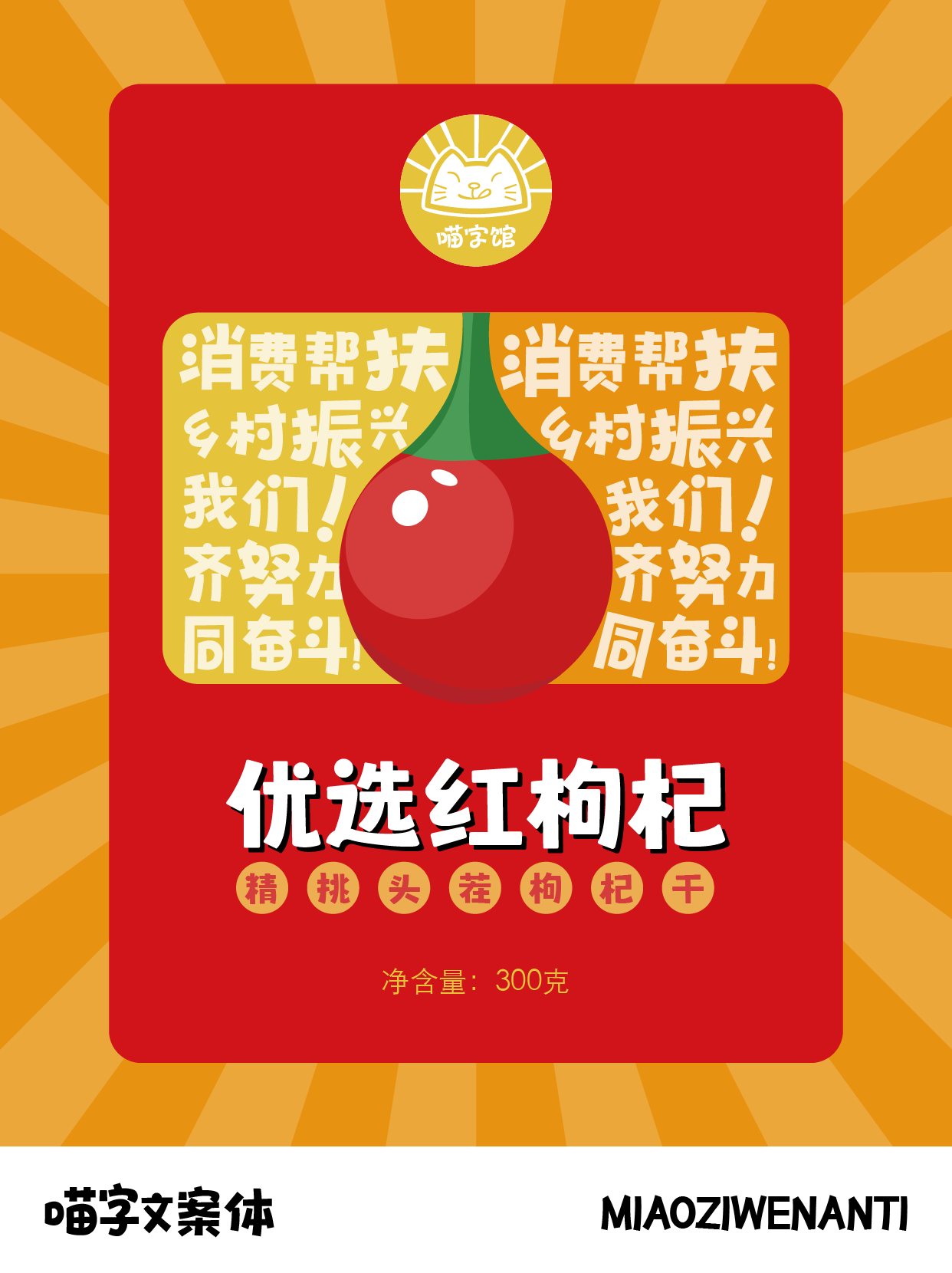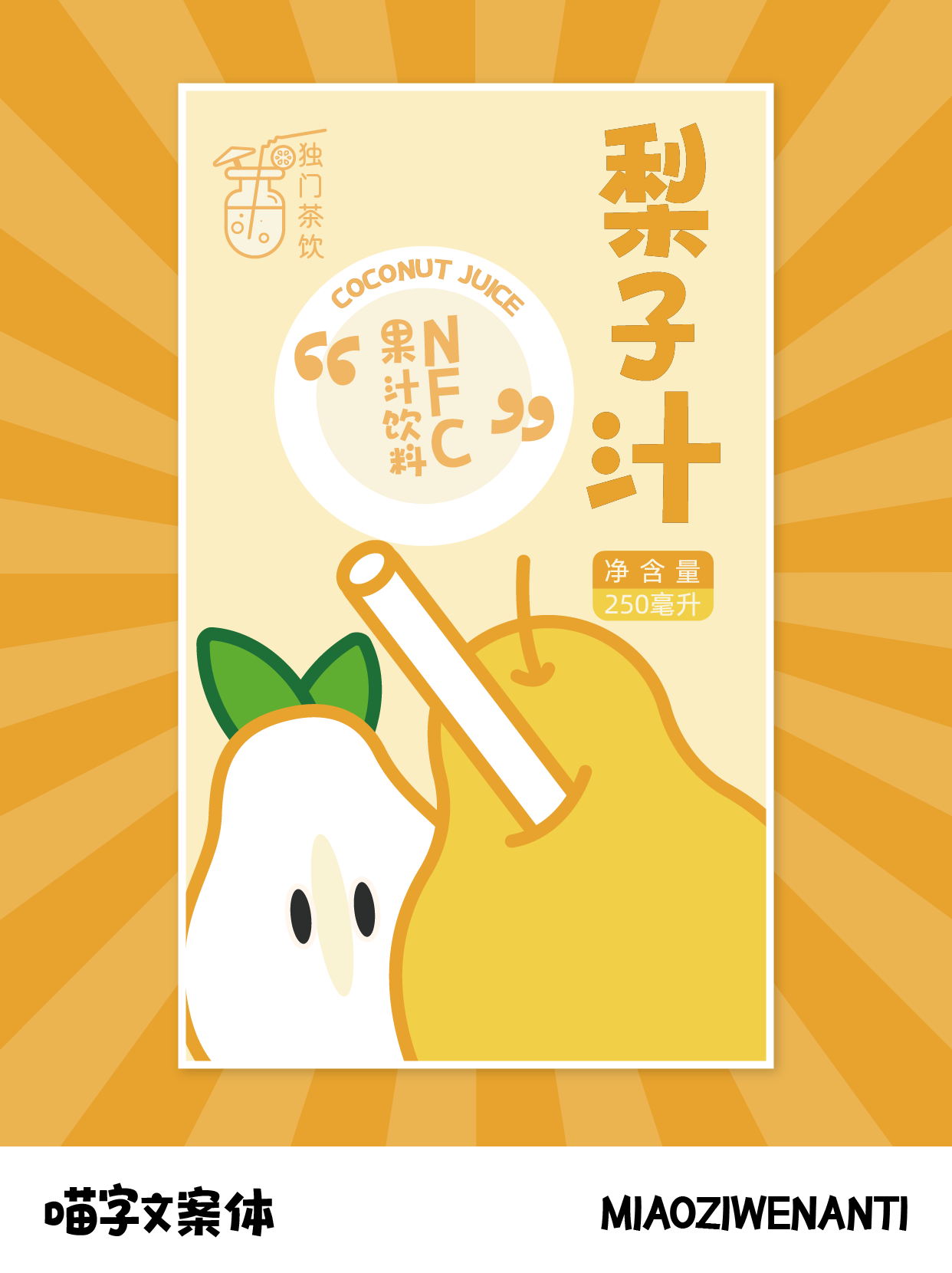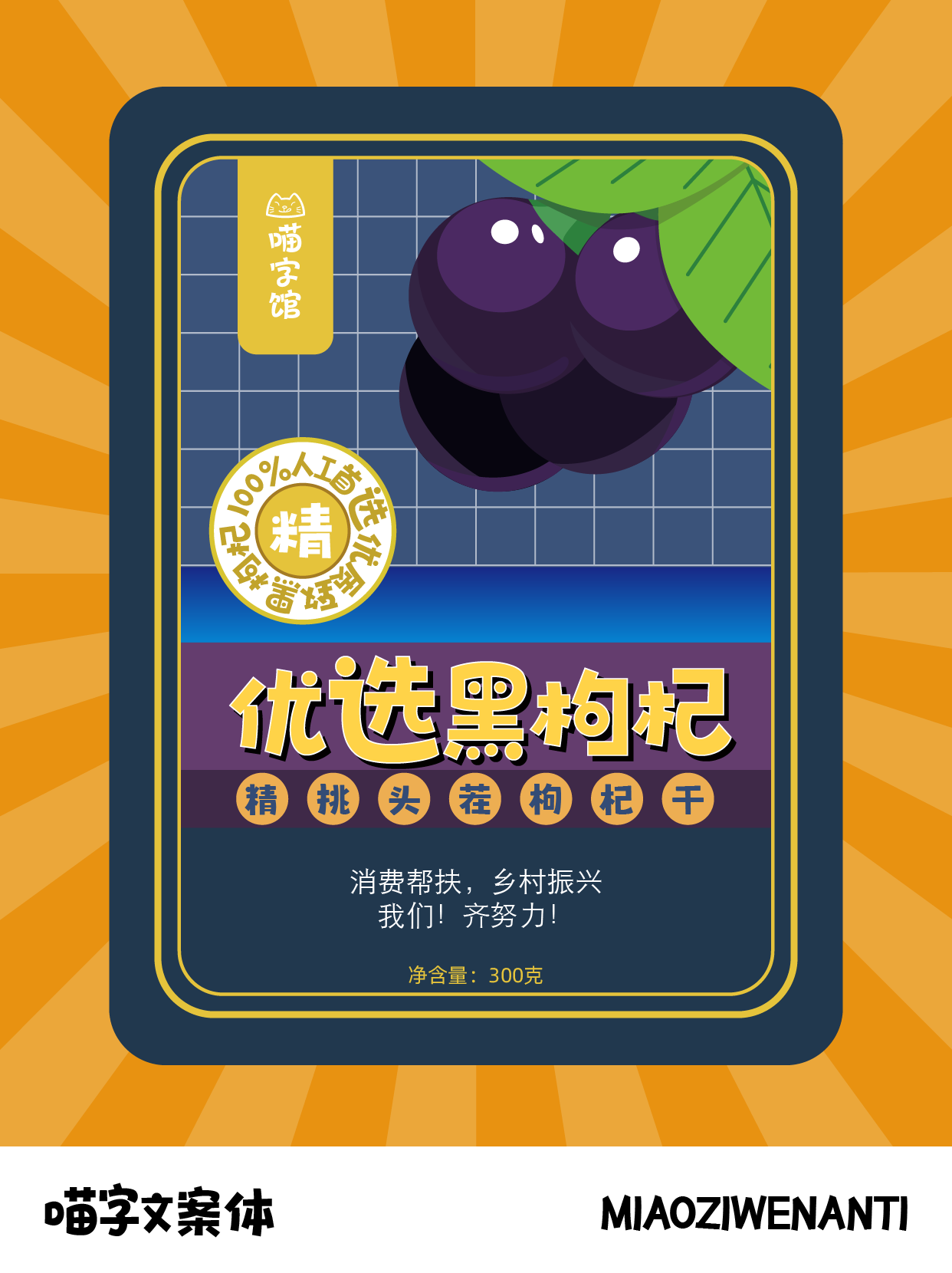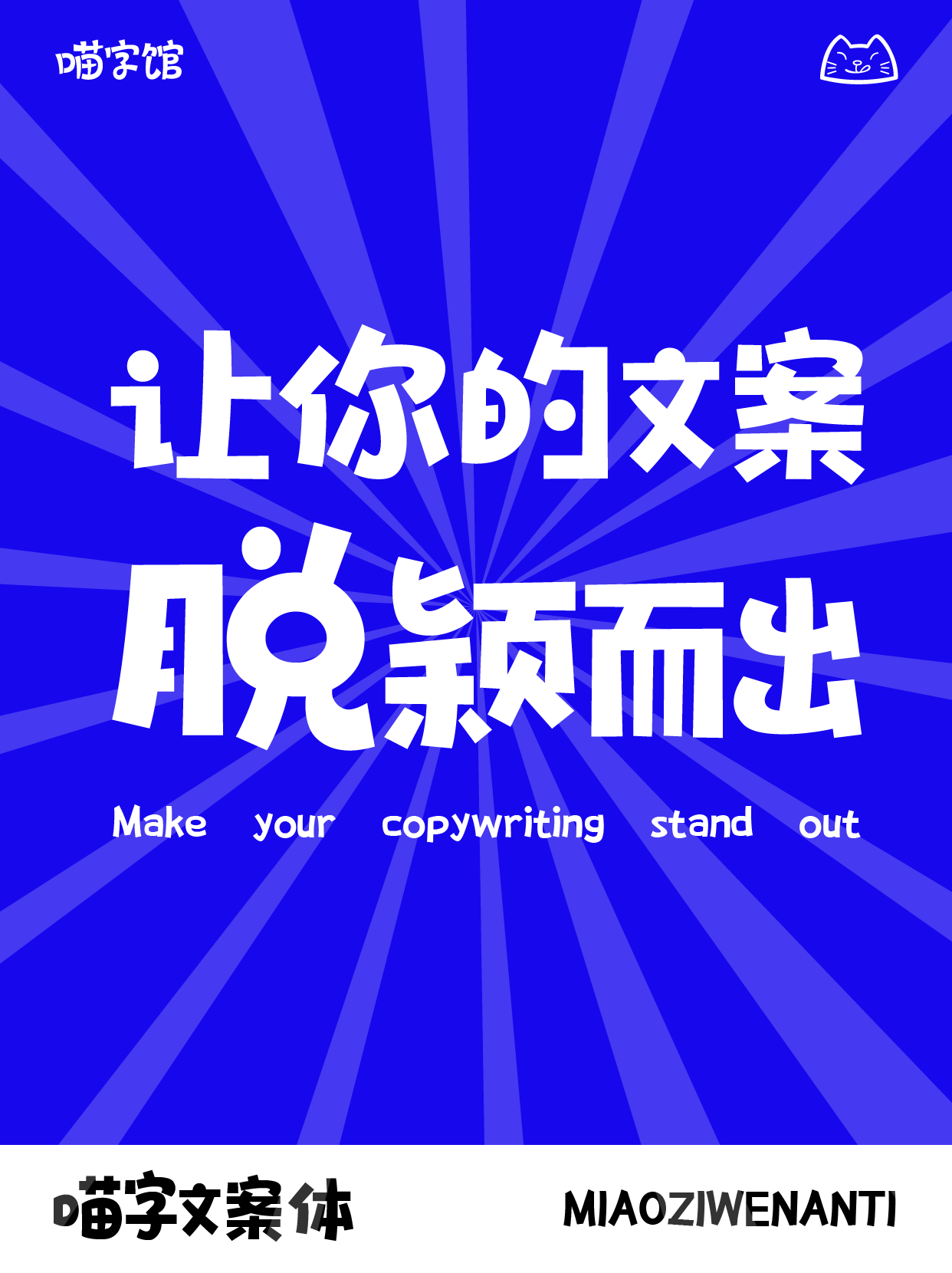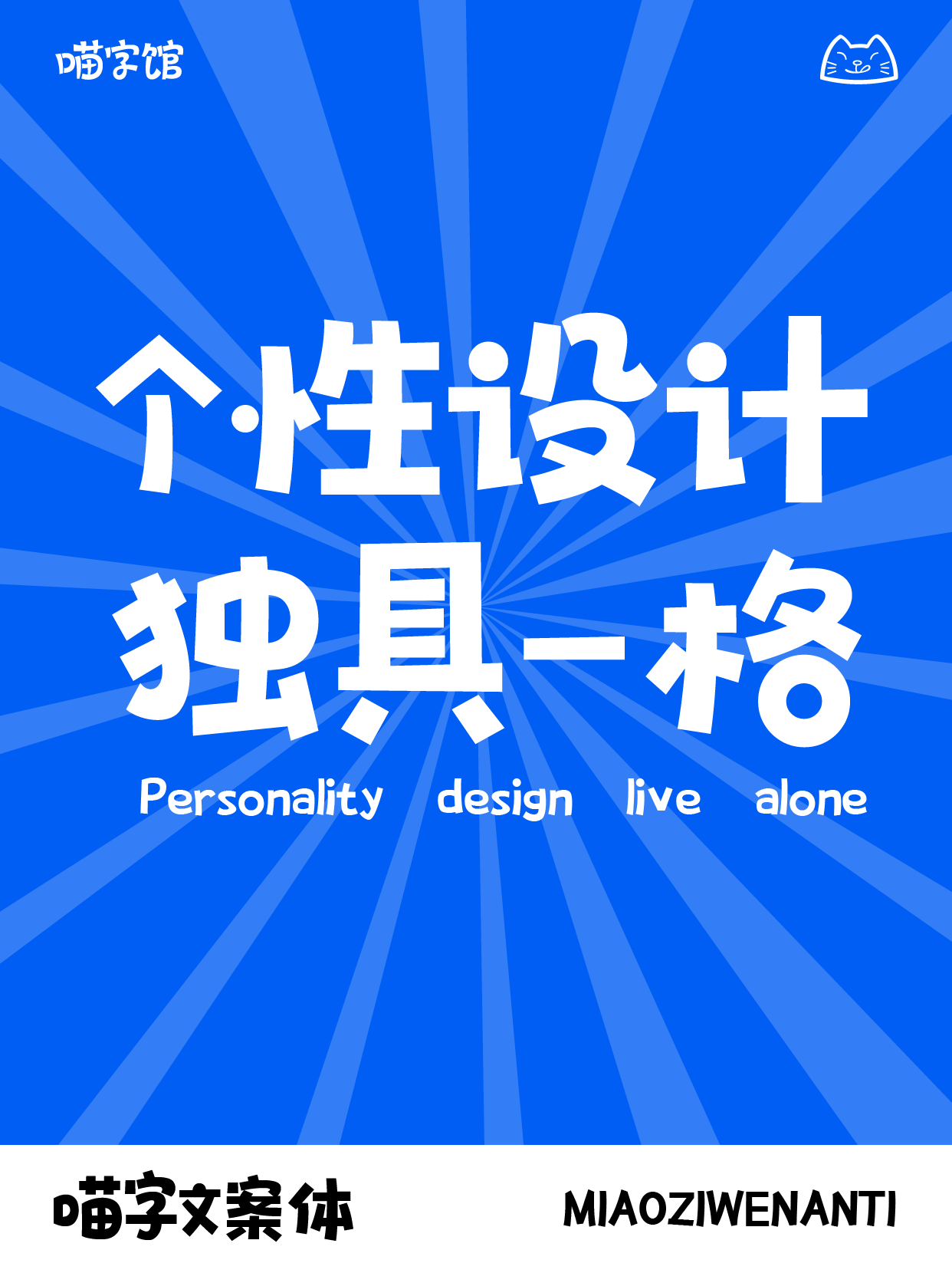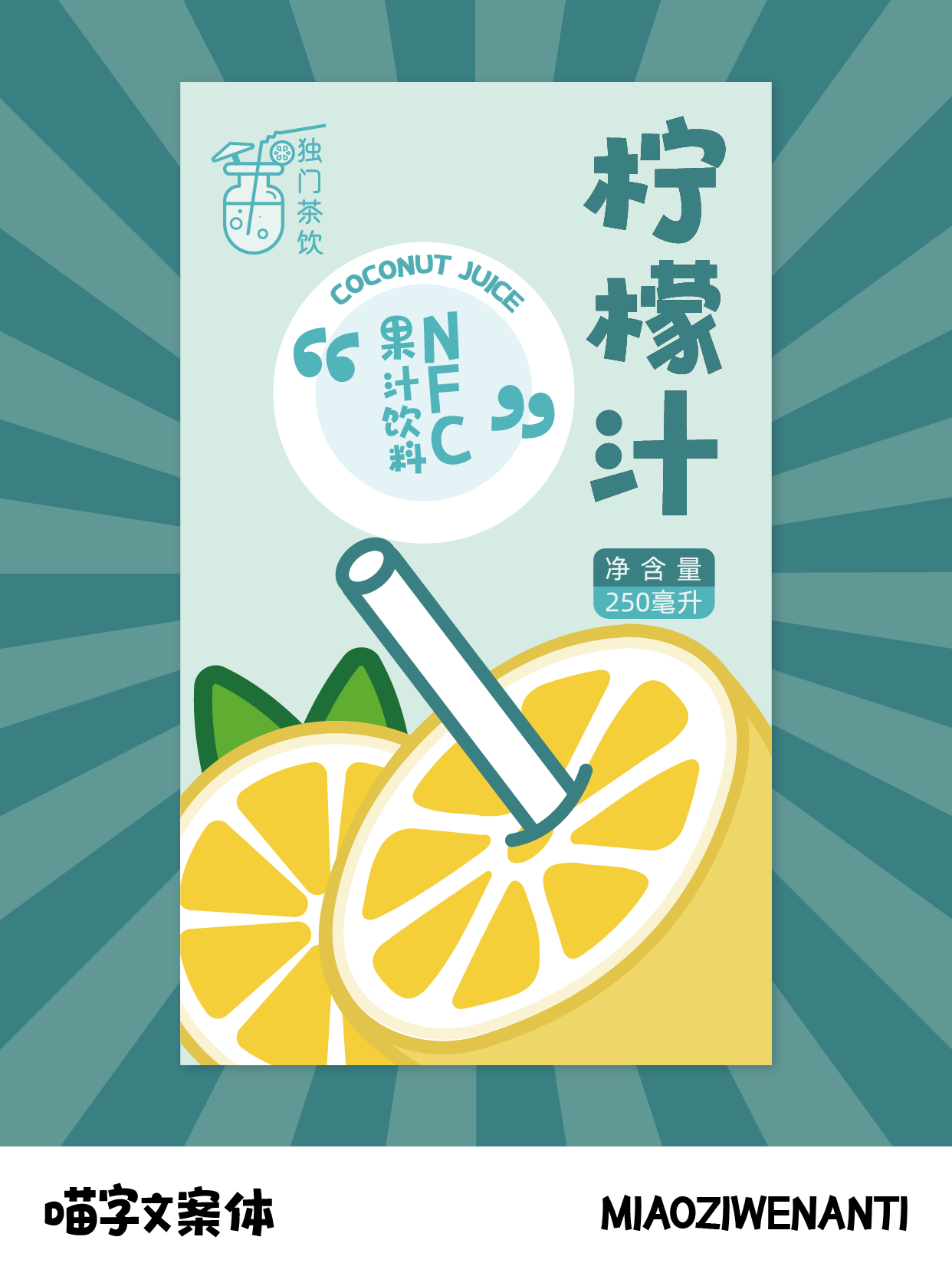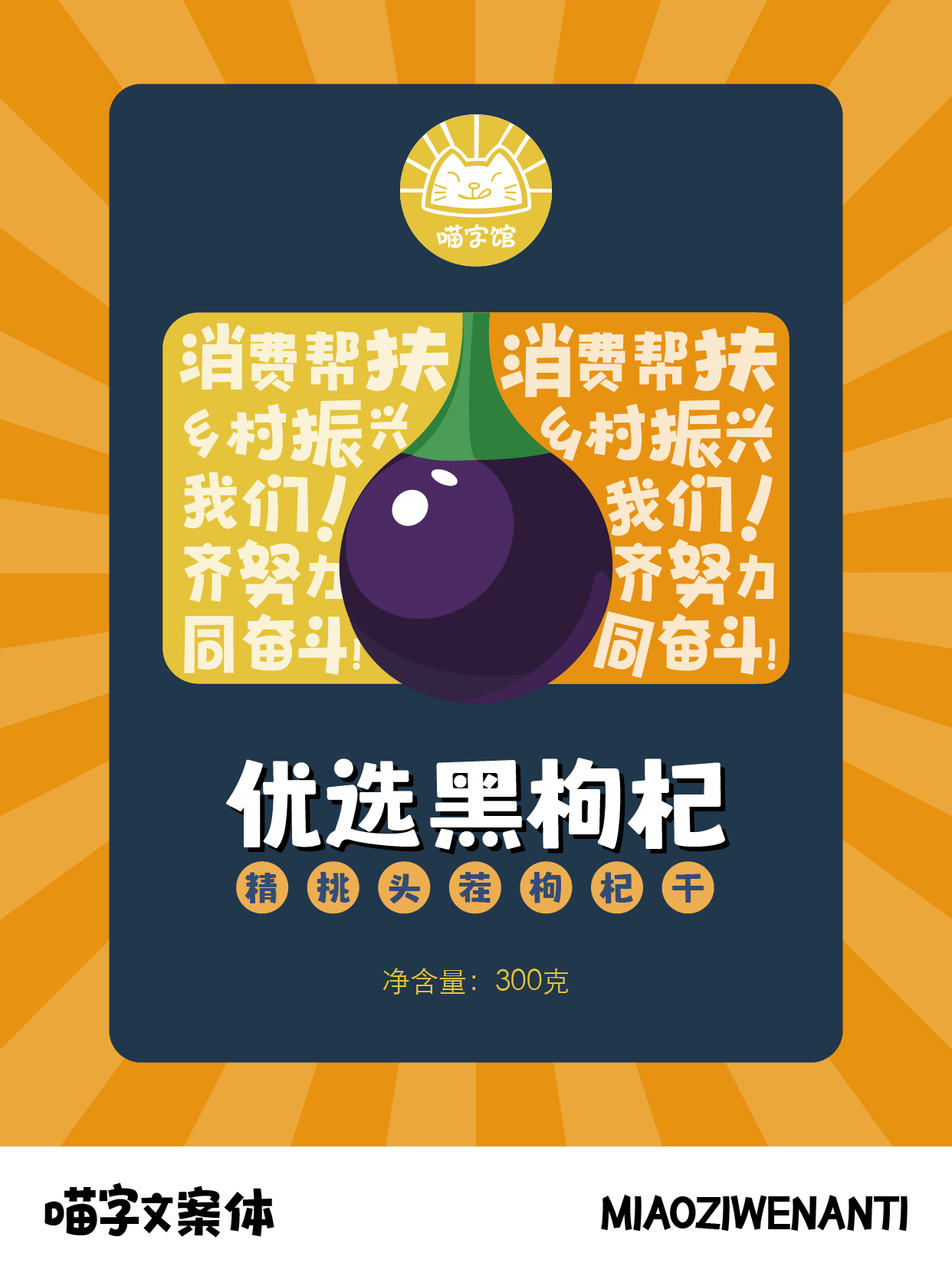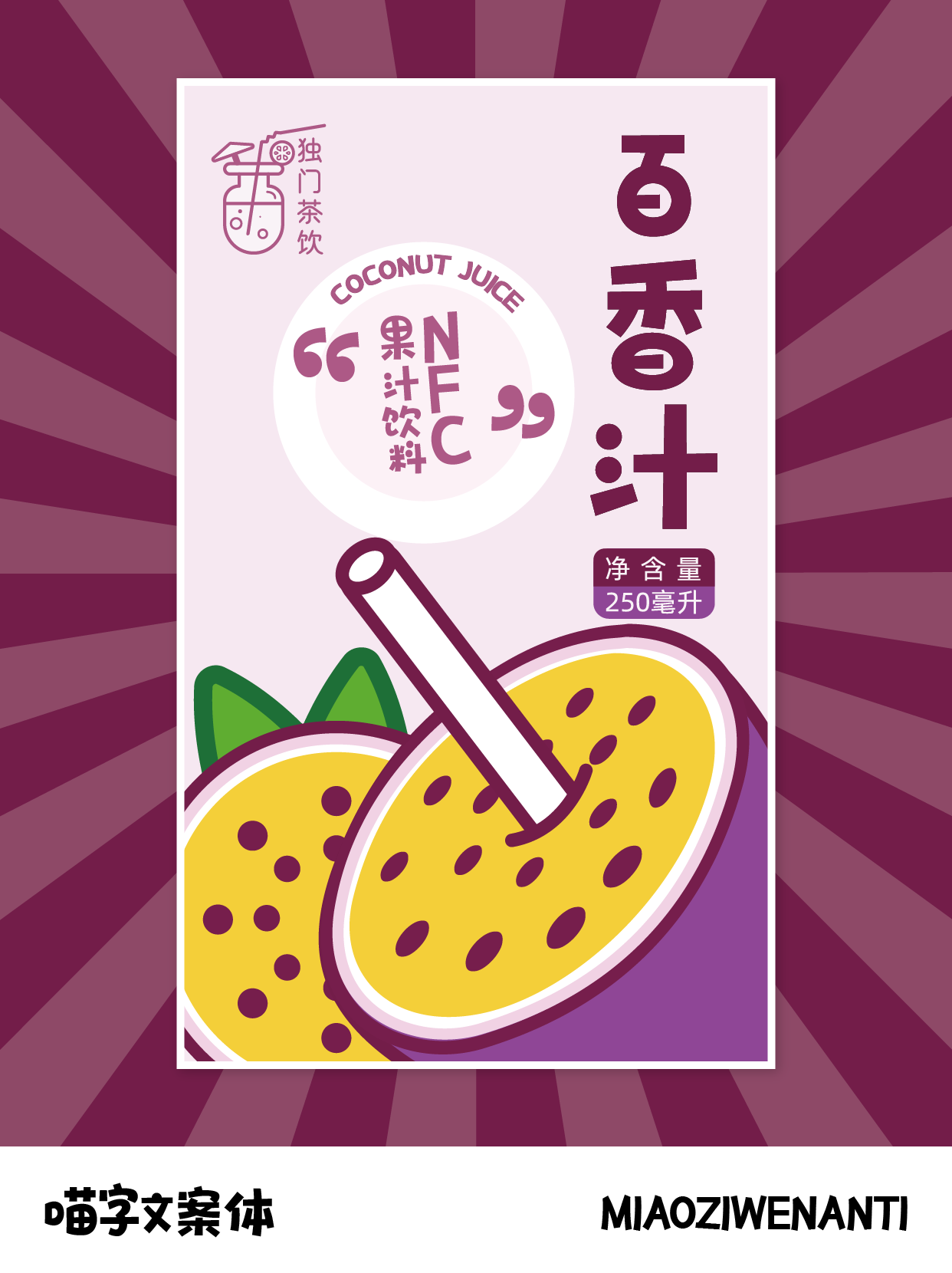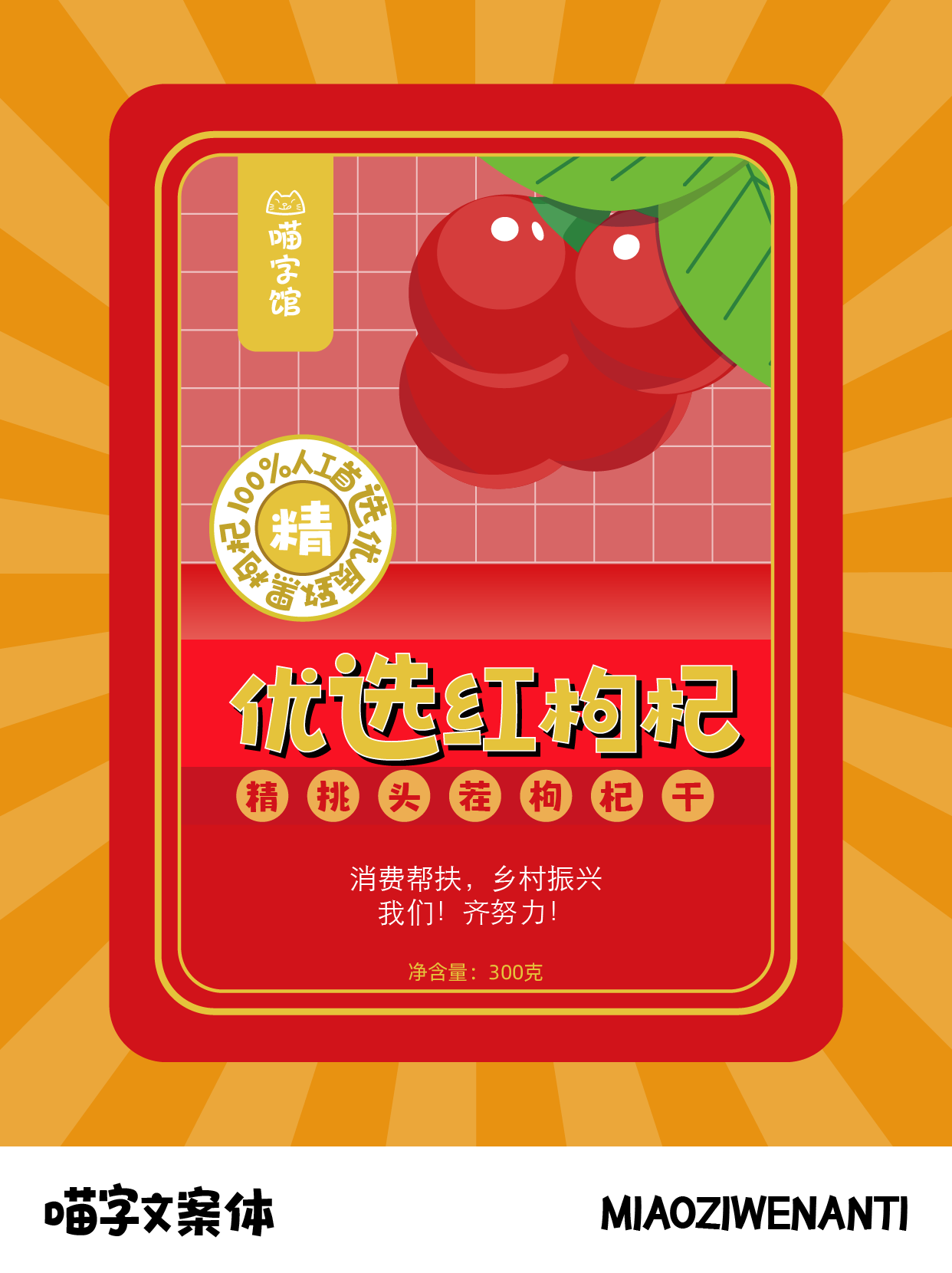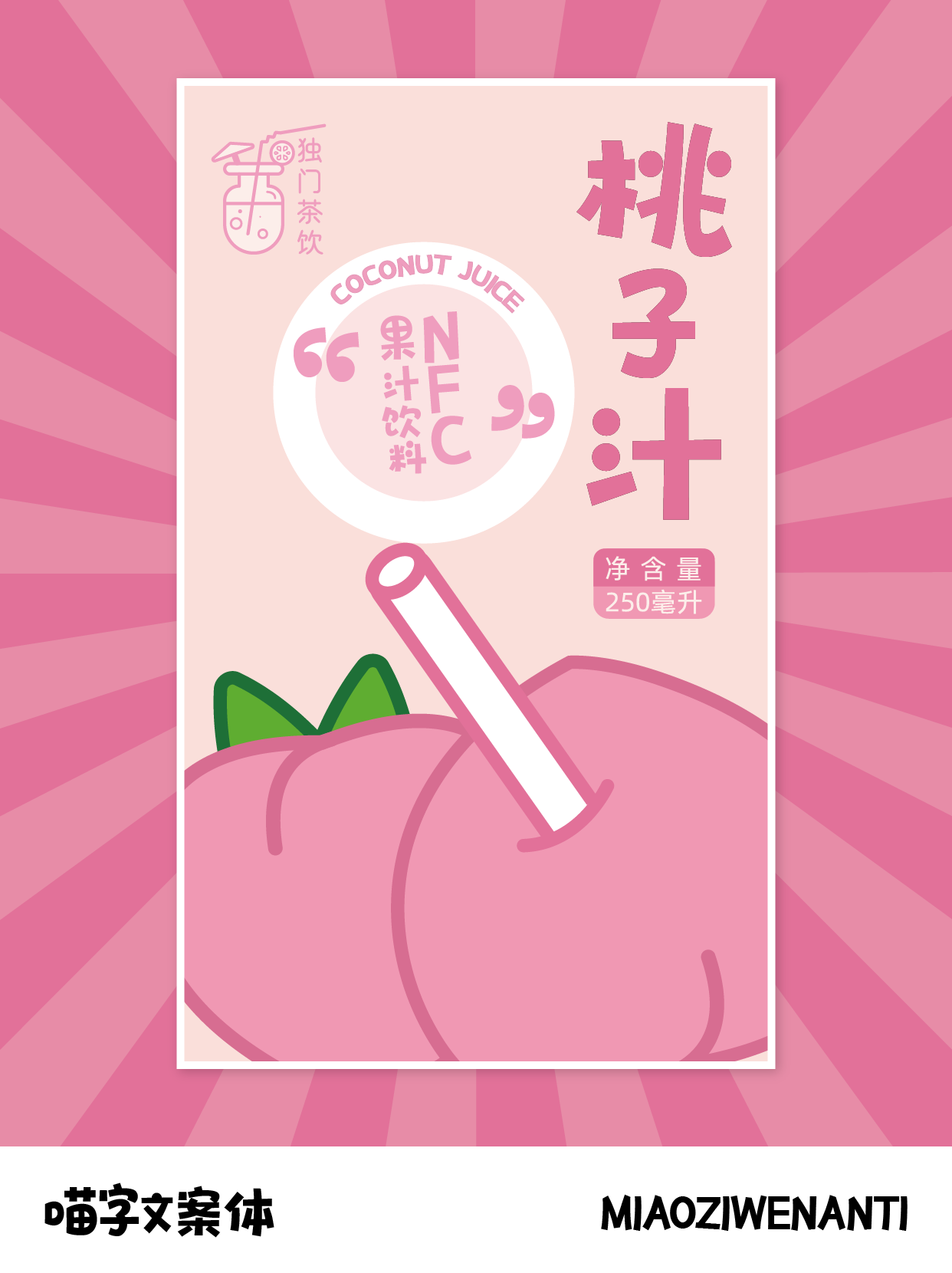
喵字文案体
MiaoZiWenAnTi
喵字文案体,是一款专为文案行业所量身打造的定制级细分字库。它巧妙融合了传统书法的韵律与现代设计的简洁,每一笔一划都透露着知性之美,旨在为文案工作者提供最贴合文字情感的视觉表达工具。此字库特别强调阅读的流畅性和视觉的舒适度,无论是广告创意、品牌故事叙述,还是社交媒体内容的编排,喵字文案体都能精准捕捉文案的精髓,赋予文字以温度和力量。